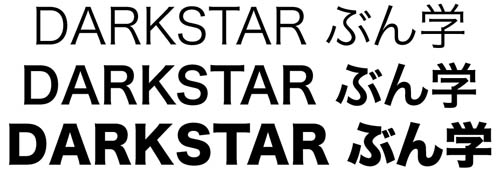
Suche für 1.buchstabe eine andere Schrift
Suche für den ersten buchstabe eine andere Schrift, benutze für den Rest "Hiragino Kaku Gothic Std" Weis auch nicht ob das soooo gut ist, aber ich finde nix besseres... Mache gerade einen Flyer, die Veranstaltung heisst " DARK STAR" und genau um die geht es. Habe bei dem Wort "STAR" das "A" in einem stern stehen, der Stern steht mit im Wort. Jetzt suche ich für den Anfangsbuchstabe von DARK ( "D" ) eine Schrift die dafür funktionieren würde, achja und eine zum kostenlosen download :oops:
das problem ist ich find keine die gut passt... :cry:
achja, die schrift Hiragino Kaku Gothic Std ist serifenlos und fett...
aber wir wissen doch nicht wie dein vorhandens "darkstar" aussieht.
warum soll denn der erste buchstabe anders aussehen? das A sieht doch schon anders aus ... reicht das nicht?
mhm...naja, stimmt, dachte nur es sieht mir noch zu langweilig aus, aber vielleicht wäre es echt zu viel! Danke für hinweis!
Hiragino Kaku ist ja eigtl. für Kana und Kanji (= Japanisch) gedacht, die lat. Zeichen müssten wie so oft aus einem anderen Font "entlehnt" sein ... weiß jemand aus welchem?
das problem ist ich find keine die gut passt... :cry:
achja, die schrift Hiragino Kaku Gothic Std ist serifenlos und fett...
nicht zwangsläufig fett: